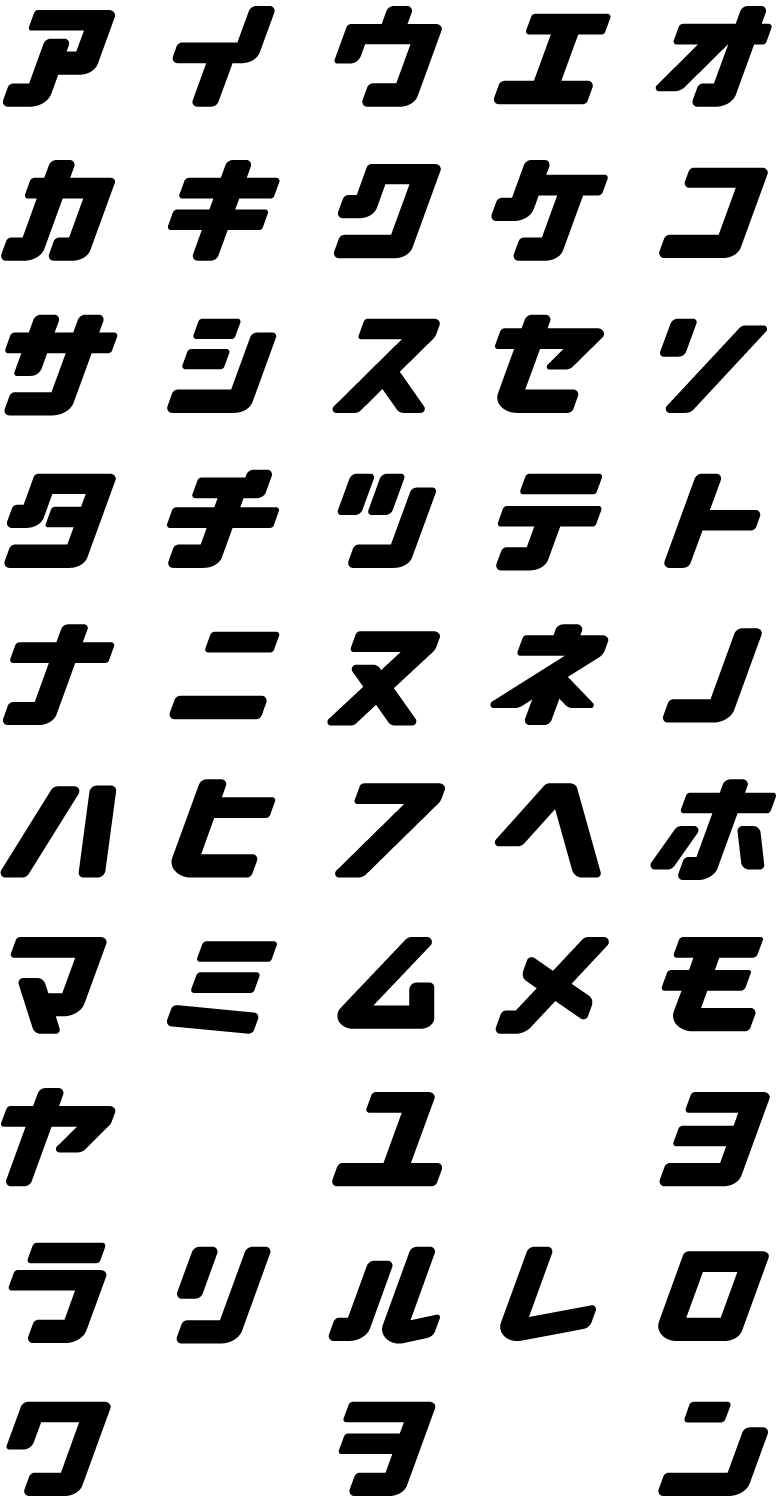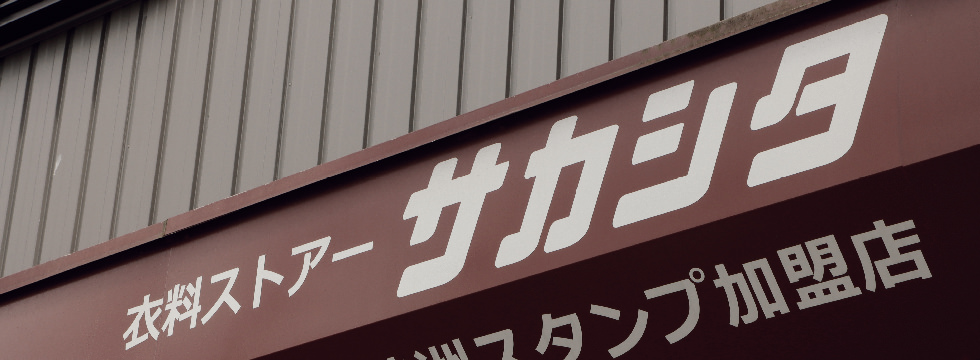
斜めになった明快なカタカナがレトロな印象だ。文字の角のRのサイズが一律同じではなく、各部でRのサイズを変え、デザインの完成度を高めている。文字のラインの太さ、角のRが親しみやすさを醸成しており、看板のアクセントになっている。
「衣料ストアーサカシタ」は明治30年頃に創業し、100年以上続くお店。飯田町商店街の中心の交差点に位置している。元は「坂下雑貨店」として創業し、今の店主である坂下重雄さんで三代目になる。お店を継ぐ前には大阪の衣料品関係の会社で働いていた重雄さんは、珠洲へもどると同時にお店のイメージを変えるため改名した。内装や看板も一新し、美術大学の卒業生であった親戚に文字を作ってもらったそうだ。「当時は岐阜や大阪、東京まで、夜汽車に乗って泊まりがけで仕入れに行った。体力的にキツいこともあったけど、とてもやりがいがある仕事だった。」と話す重雄さん。現在は定期的に訪れる常連のお客さんや、フラッと訪れる方もいる。「お客さんの世間話や相談ごとを聞きながらお店をやっていると、話したらスッキリした、また来るよ、と言ってくれるお客さんもいる。ひとつの社交の場みたいな感じでね。何かひとつほしいなって、ふっと思った時に来ていただければ。」体が動く限り続けるつもりだそうだ。
“Clothing Store Sakashita” was founded around 1897 and has been in business for over 100 years. It is located at the intersection in the center of the Iida-machi shopping district. Originally founded as “Sakashita general store,” the current owner, Shigeo Sakashita, is the third generation. Before taking over the shop, Shigeo worked for a clothing company in Osaka, but upon returning to Suzu, he changed the name of the store to change its image. He changed the interior and signage and asked a relative who was a graduate of an art university to create the sign for his shop. “In those days, I would take night trains to Gifu, Osaka, and Tokyo to stock up. It was physically demanding at times, but it was very rewarding work,” he said. Today, there are regular customers who visit the store regularly, as well as those who come by on a whim. “Some customers tell me that they feel refreshed after talking with me and that they will come back again. It is such a place for socializing something like. I hope people will come here when they feel like they need a little something.” He says he plans to keep doing this as long as he is physically able.